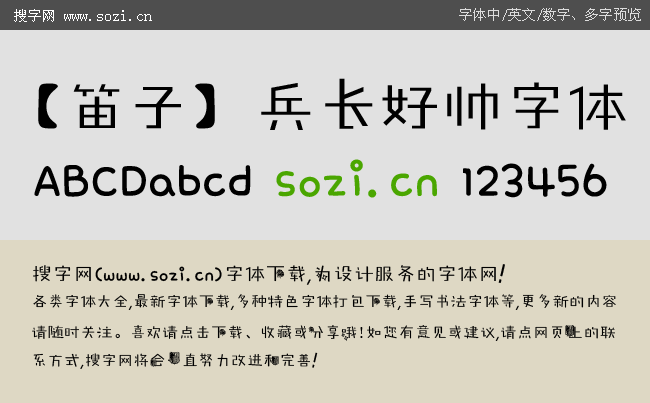
兵長(zhǎng)好帥字體
搜字網(wǎng)給大家提供一款卡通手寫風(fēng)格的手機(jī)中文字體下載。名字叫兵長(zhǎng)好帥字體,這款手機(jī)字體是仿照兒童手寫風(fēng)格的卡通手寫字體,結(jié)構(gòu)帶有POP字體風(fēng)格,個(gè)別筆畫還替換成了卡通圖案。特別適合喜歡卡通的朋友在手機(jī)上安裝使用。